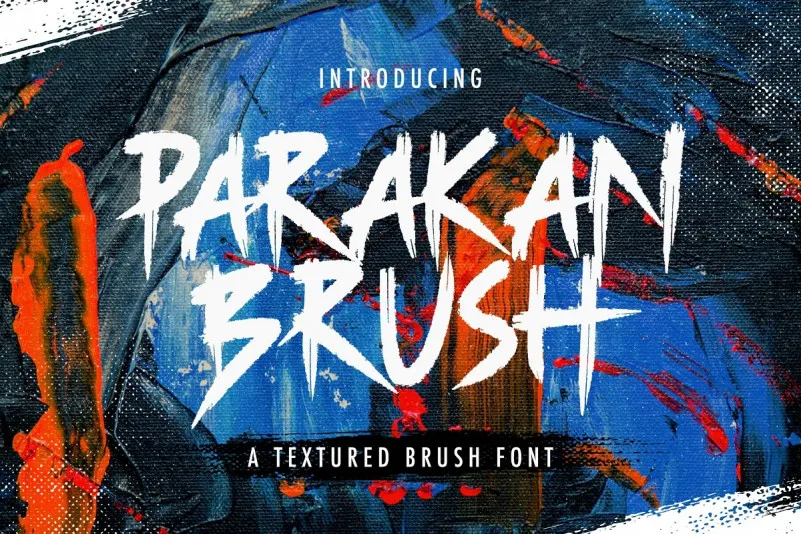
Parakan Brush Font – Download Grátis
A Parakan Brush Font é uma opção vibrante para designers que desejam dar vida a seus projetos com um estilo único e versátil. Esta fonte display exibe traços suaves e finos, criando uma impressão amigável e envolvente. Combinada ao seu conjunto de caracteres, essa fonte oferece uma variedade impressionante para criar designs impressionantes e surpreendentes. Para aqueles que buscam um toque único em suas aplicações digitais ou impressas, a Parakan Brush Font é um recurso indispensável, perfeita para quem procura uma paleta de opções não convencional. Como resultado da colaboração entre StringLabs e o 99designs, essa fonte está disponível para que designers possam experimentar seu incrível potencial.